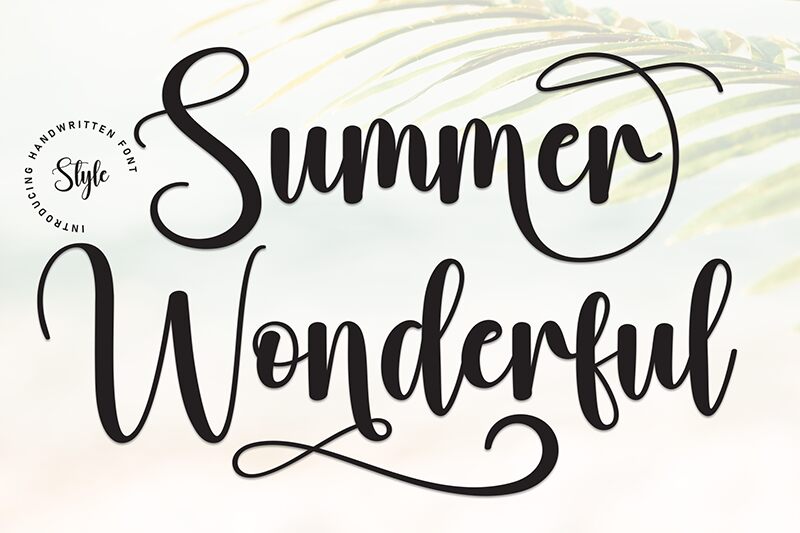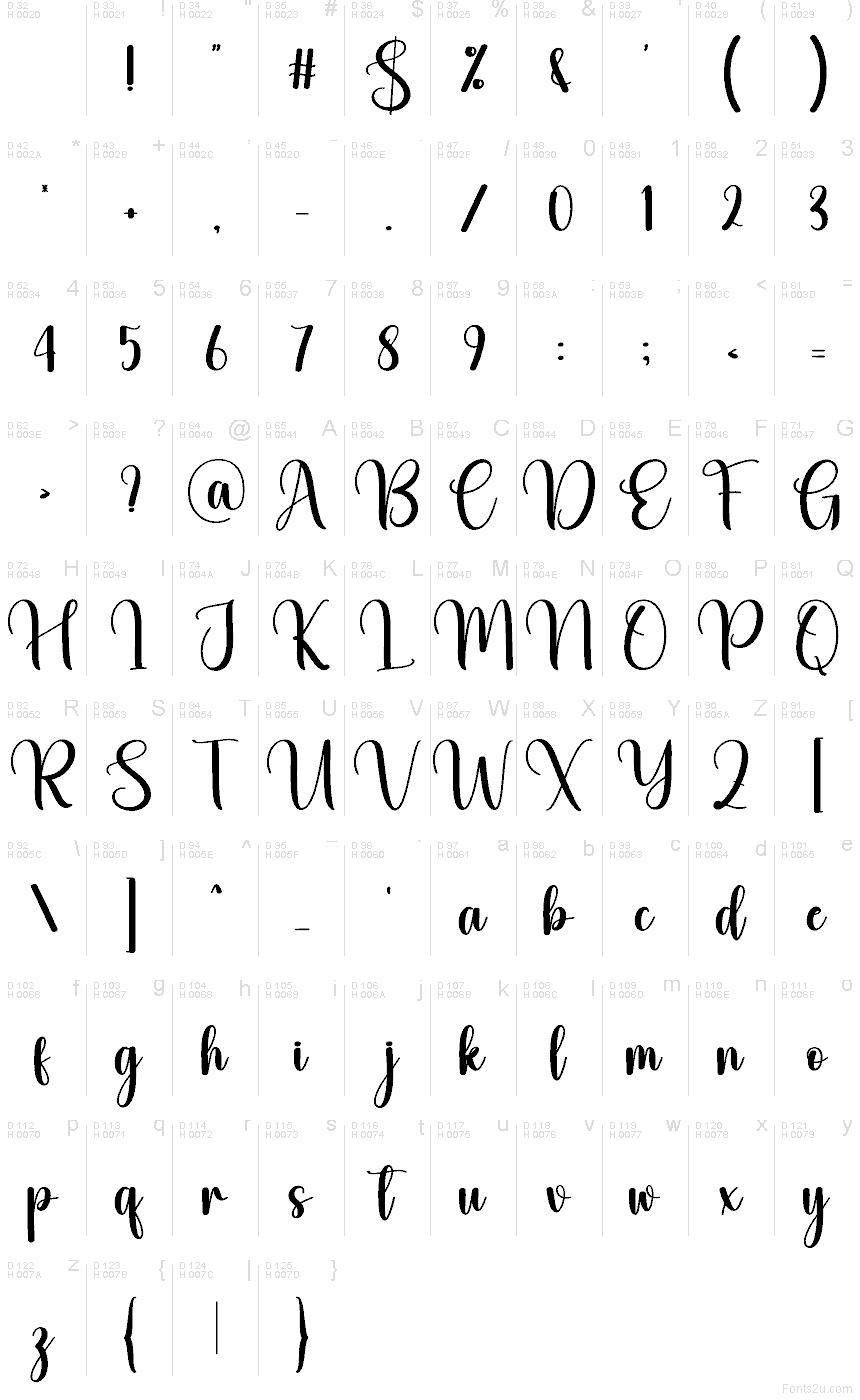
Summer Wonderful est une police de calligraphie moderne et gratuite au rendu pinceau fluide. Construite autour de ligatures douces et de grandes boucles, elle insuffle un rythme estival et décontracté au lettrage. Ses caractères mêlent des traits arrondis et pleins à des courbes hautes et étroites, conférant à l'ensemble un esprit fait main, authentique et sans fioritures.
Elle s'intègre naturellement dans l'identité de boutiques, la papeterie de mariage, le packaging de cafés, les en-têtes de réseaux sociaux ou les titres de magazines où un peu de mouvement est nécessaire. En tant que police gratuite, elle fonctionne aussi très bien pour de courts titres, des invitations ou des esquisses de logos, surtout quand vous recherchez une lettrine élégante qui s'étire harmonieusement sur le reste du mot.
Présentation et spécimen de la police Summer Wonderful
Table des caractères de la police Summer Wonderful
Table des caractères de Summer Wonderful : Latin de base, page 1
Glyphes de la police Summer Wonderful — Latin de base, page 1
Summer Wonderful